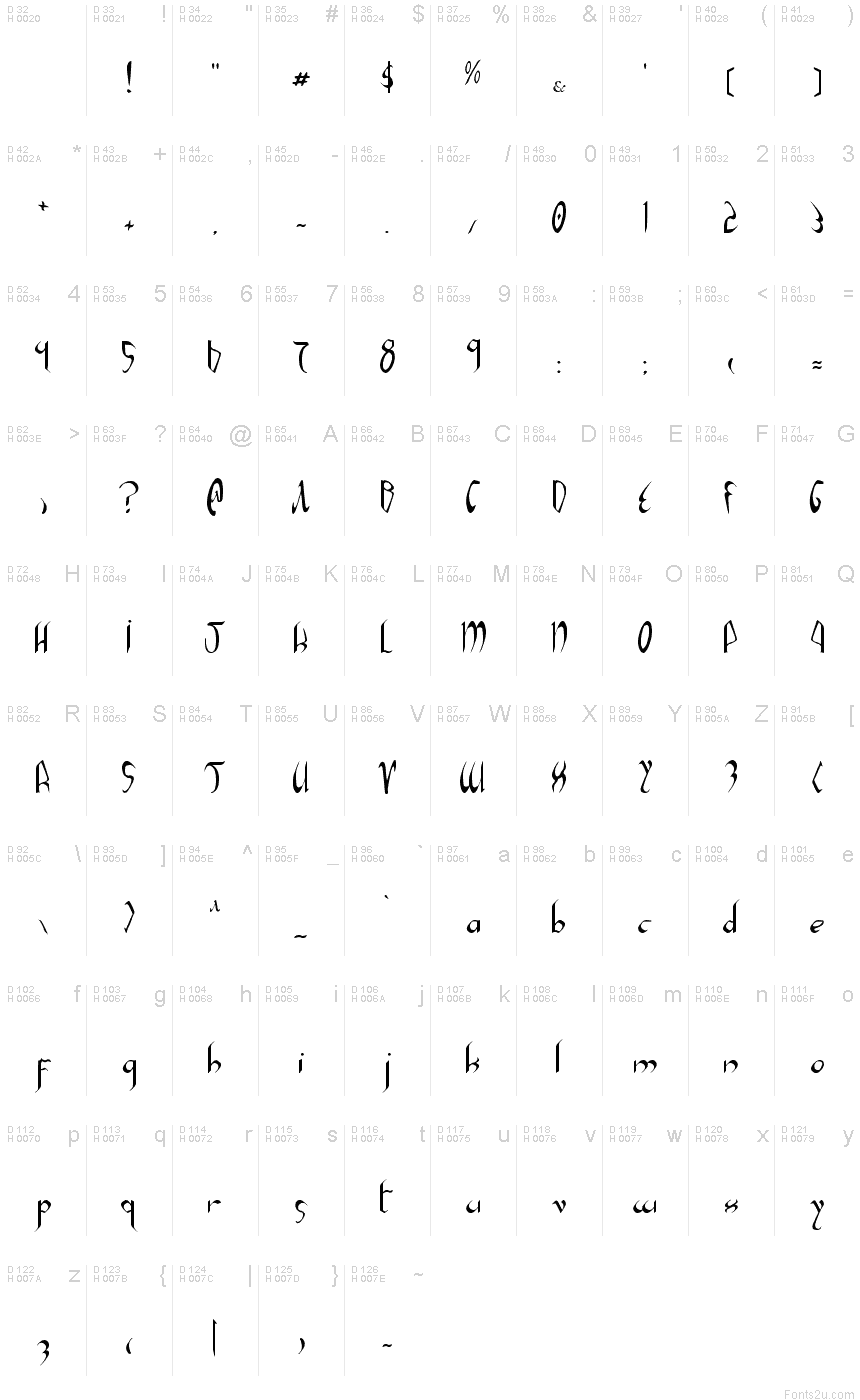
Podgląd czcionki Xaphan
Xaphan od Iconian Fonts to darmowy krój typu gothic display o mrocznym, rytualnym nastroju i wyraźnie średniowiecznym klimacie. Litery łączą w sobie cechy pisma łamanego (blackletter) z ostrzejszymi, niemal przypominającymi pazury cięciami, dzięki czemu słowa wyglądają, jakby były oświetlone blaskiem świec, a nie wygładzone do dworskiej elegancji.
Krój naturalnie sprawdza się na ulotkach metalowych, okładkach książek fantasy, w tytułach gier, okultystycznym brandingu i nagłówkach plakatów, gdzie atmosfera jest ważniejsza od neutralności. Wykorzystaj go do krótkich nazw, początków rozdziałów, logotypów zespołów czy inicjałów w stylu monogramu, jeśli zależy Ci na surowym, dawnym charakterze – ostre kreski i gwałtowne krzywizny nadają nawet krótkim tekstom naładowaną, ceremonialną obecność.